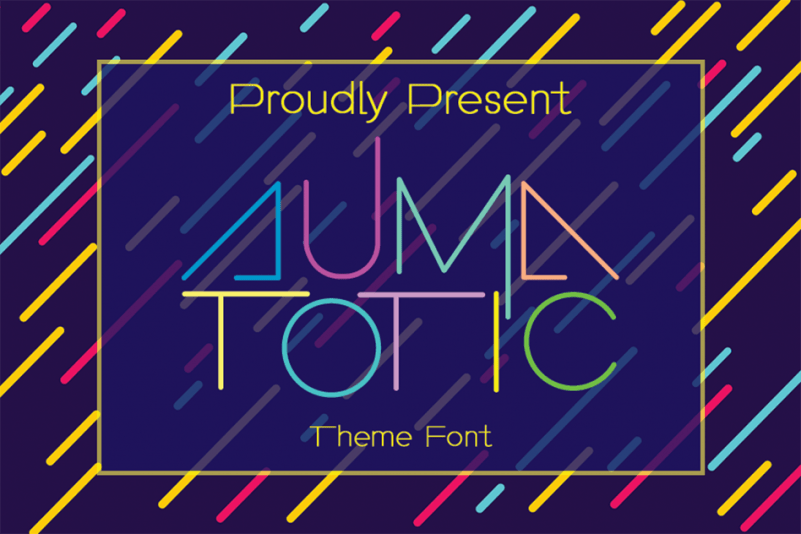
A “Automatic Display Font” é uma opção elegante para designers que desejam adicionar um toque moderno e minimalista a seus projetos digitais. Especificamente concebida como uma fonte de display, ela é ideal para criações web avançadas, cartões de visitas empresariais ou qualquer projeto em que seja necessário apresentar uma presença única. Suave e linear, esta fonte complementa o estilo moderno com linhas finas, tornando-a perfeita para aplicativos gráficos digitais, como banners, websites profissionais, e design de aplicativos móveis. A “Automatic Display Font” é a escolha ideal para quem procura uma maneira criativa de personalizar seus designs digitais.